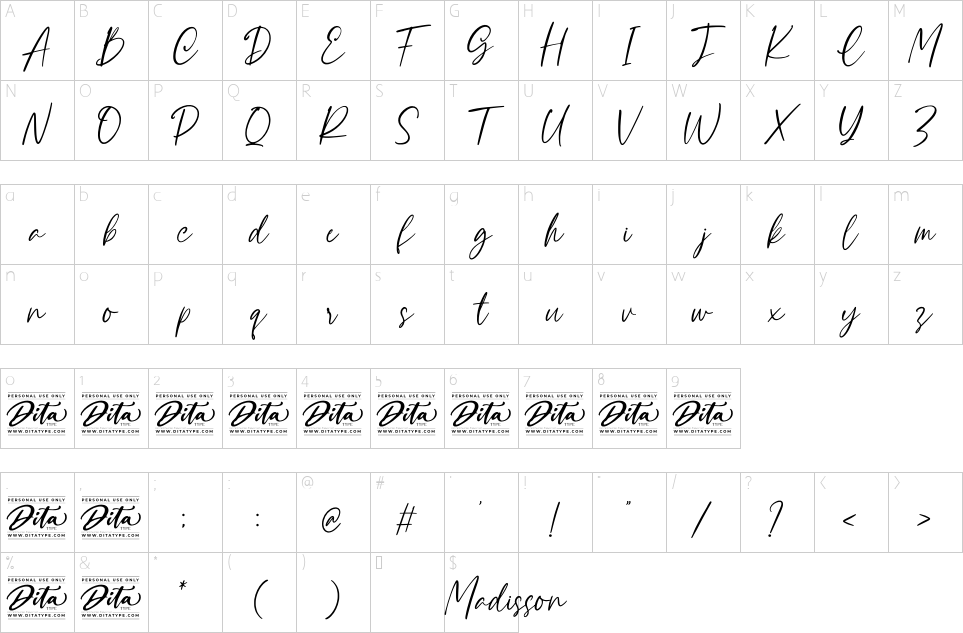
A Madisson font é uma grata surpresa para os designers que buscam graciosas e elegantes letras para suas projetos. Desenhada por Dita Type, essa fonte está disponível gratuitamente tanto para Windows quanto para Mac. Com seu design minimalista e sofisticado, a Madisson é perfeita para textos em blogs, websites e pequenos projetos pessoais. A fonte tem se destacado com sua facilidade de uso e variedade de opções de estilo, tornando-a uma escolha conveniente para qualquer projeto gráfico. Desde que foi lançada, a Madisson foi baixada mais de 3.080 vezes, indicando o quanto o design de sua fonte é apreciado. Se você está procurando por uma fonte com estilo e qualidade, a Madisson é uma ótima escolha.